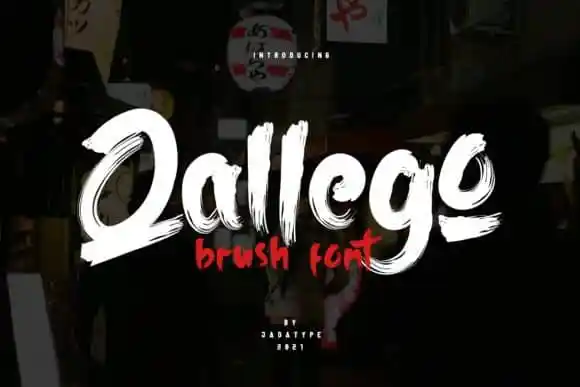
Qallego Brush Font – Download Grátis
A Qallego Brush Font é uma nova tipografia feita especialmente para designers que buscam incorporar um toque único e encantador aos seus trabalhos. Ela traz texturas de grafite perfeitamente impressas, criando um contraste interessante que enriquece qualquer projeto gráfico. Este tipo de fonte única foi fabricada pela JadaType, conhecida por criar tipografias exibicionistas e revolucionárias. Com a Qallego Brush Font, seus designs ganham uma aparência jovial e vibrante que pode ser usada para criar arte sofisticada de cartão de visita, postagens capturadoras em redes sociais e muito mais. Uma fonte como esta é perfeita para aqueles desejosos de inovar e explorar diferentes estilos visuais no seu trabalho.